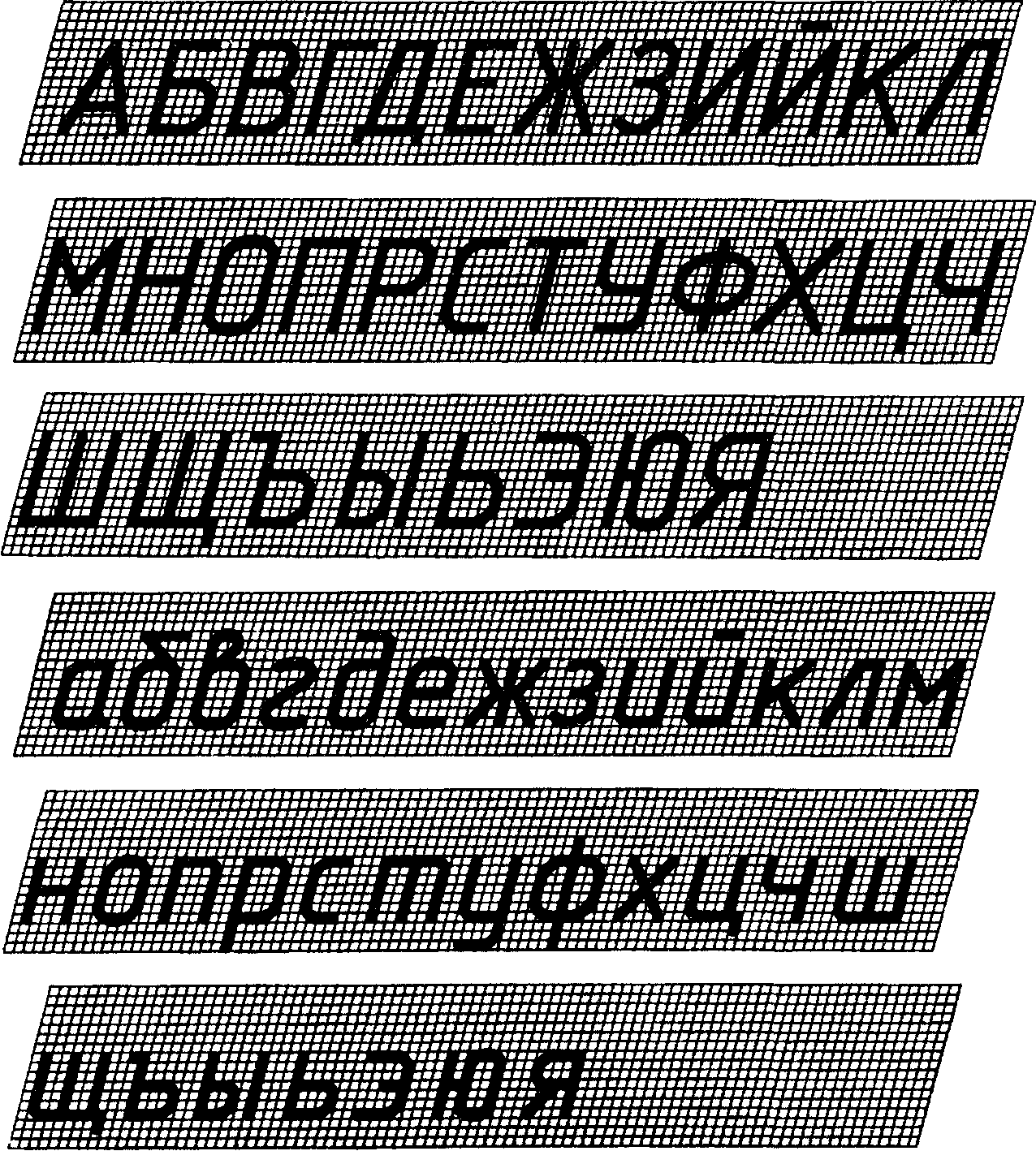
Шрифт по ГОСТ 2.304-81 тип А
Скажите, а узкий архитектурный шрифт никто сделать не пробовал?
Шрифт лучше использовать в однострочном тексте, насколько я знаю в Mtexte всегда были проблемы с рускими буквами.
Ребята. Не парьтесь рулите на ISOCPEUR. Есть на любой операционке, похож на ГОСТ-овский, поддерживает надстрочные и подстрочные символы, не глючит в редакторе мультитекста, ширину текста как и любого другого измените при надобной нужности при форматировании шрифта в самом каде. Шо вы ищете приключения на пятую точку опоры.
semvb , 22 августа 2005 в 15:57 #7 Шрифт вполне пригоден для написания текстов по ГОСТ. Но хотелось бы добавить несколько символов. К сожалению не получается сконвертировать shp в shx/ АКАД выдает Invalid shape element, or bad syntax.
Все отлично, но только значок в MTEXT не могу вывести №(номер), не выводится как не пробывал
Можно ли на этих шрифтах набить верхние и нижние индекы, ну там типа КВАДРАТ, КУБ и т.д. %%168 %%169
[c.363] Оформление рабочего чертежа. Независимо от конструкторского или технологического вида детали ее чертеж должен быть оформлен с соблюдением требований стандартов, определяющих форматы, масштабы, линии и шрифты [см. ГОСТ 2.301 -68 (СТ СЭВ 1181-78) Форматы , ГОСТ 2.302-68 (СТ СЭВ 1180-78), Масштабы, ГОСТ 2.303-68 (СТ СЭВ 1178-78) Линии ГОСТ 2.304-81 (СТ СЭВ 851 -78… СТ СЭВ 855-78) Шрифты чертежные ]. [c.224]
Шрифты чертежные.
В различных отраслях науки и техники применяют самые разнообразные шрифты (букв, цифр, условных знаков).
Шрифты чертежные — ГОСТ 2.304—81. [c.12]
Шрифты чертежные ГОСТ 2.304 – 81. [c.38]
ГОСТ 2.304—81 (СТ СЭВ 851—78, СТ СЭВ 855 -78). Шрифты чертежные. [c.213]
Шрифты чертежные ГОСТ 2.304—81 (СТ СЭВ 851—78, [c.224]
Надписи, наносимые на чертежи и другие технические документы, должны выполняться стандартным шрифтом. Чертежные шрифты для всех отраслей промышленности и строительства устанавливает ГОСТ 2.304—81 (СТ СЭВ 851—78— СТ СЭВ 855—78). [c.40]
Шрифты чертежные (по ГОСТ 2.304—81). Размер шрифта определяется высотой прописных букв в миллиметрах 2,5 3,5 5 7 10 14 20 28 40.
ШРИФТ ЧЕРТЕЖНЫЙ (по ГОСТ 3454—59) [c.14]
ШРИФТ ЧЕРТЕЖНЫЙ П родолжение [c.15]
Шрифты чертежные. ГОСТ 2.304-81 установлено 9 размеров чертежных шрифтов 2,5 3,5 5 7 10 14 20 28 40. Наиболее употребительны размеры шрифта от 3,5 до 14. [c.33]
НИИ сгиба (рис. 24) и частей изделий в крайних или j 5 ШРИФТЫ ЧЕРТЕЖНЫЕ промежуточных положениях, а также для изображения развертки, совмещенной с видом. На рис. 25 Надписи на чертежах выполняют от руки шриф-показано применение штрихпунктирной тонкой ли- том по ГОСТ 2.
Бее нядинси на чертежах следует выполнять шр фтами, установленными ГОСТ 2.304-81 (СТ СЭВ 851—78 – СТ СЭВ 855-78) Шрифты чертежные . Шрифты различа-iOi по размерам и ишам. [c.4]
При построении сетки для строчных букв нужно учесть, что высота строчных букв составляет 7/10 h. Необходимо помнить, что прописные и строчные буквы имеют различную ширину.